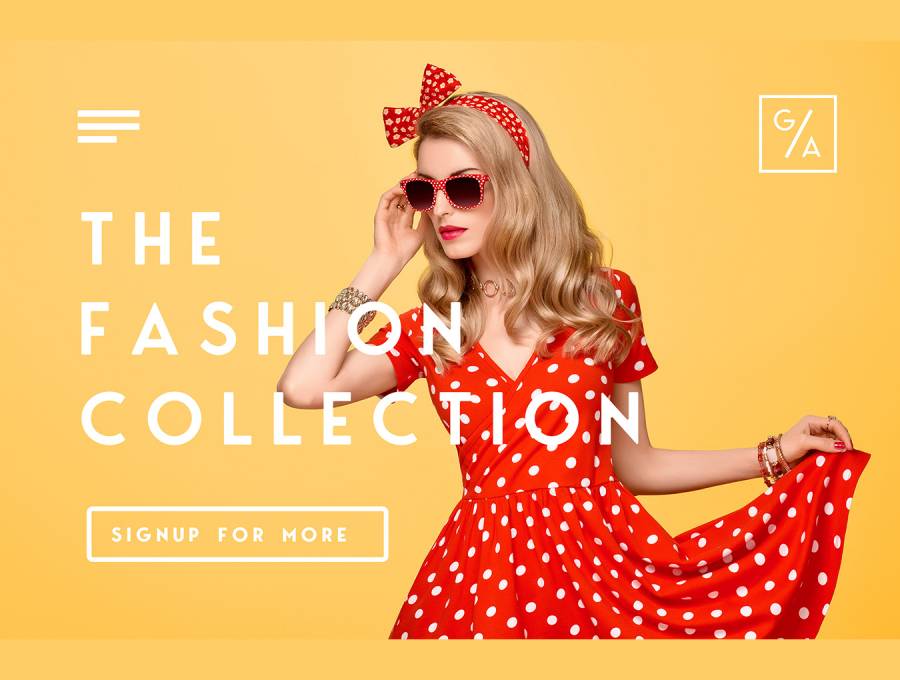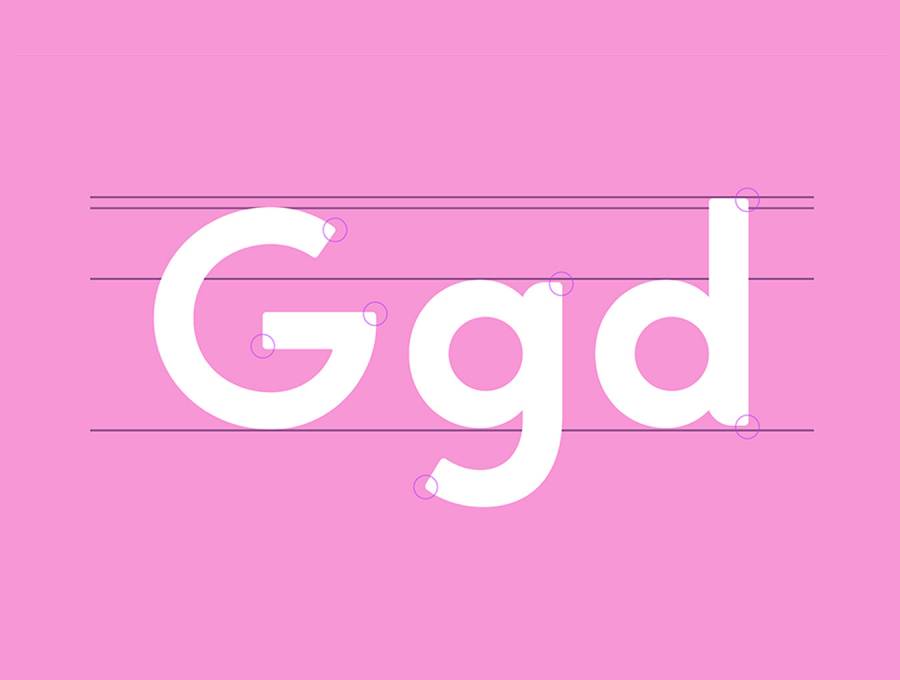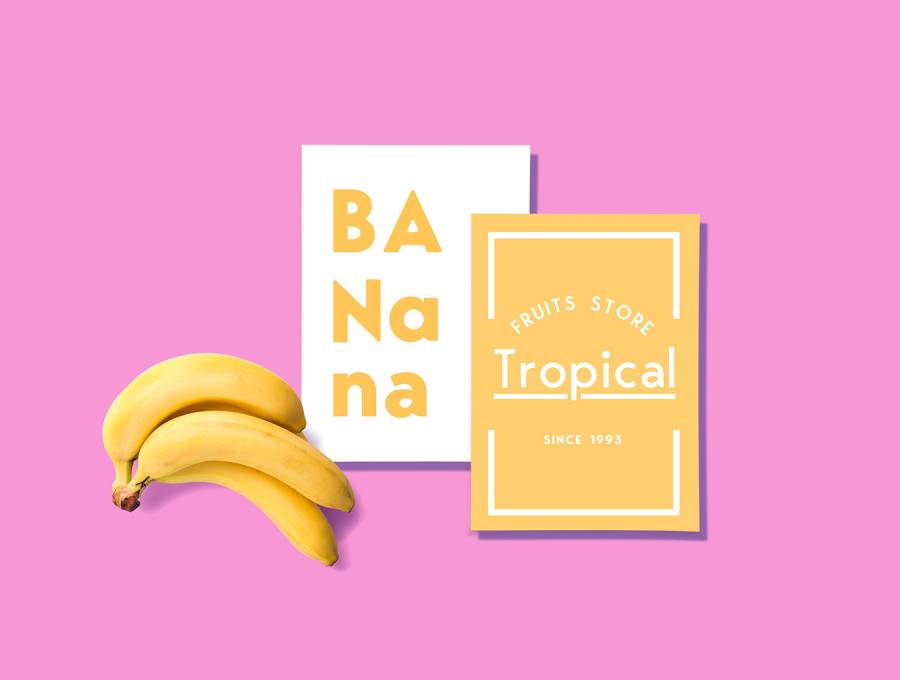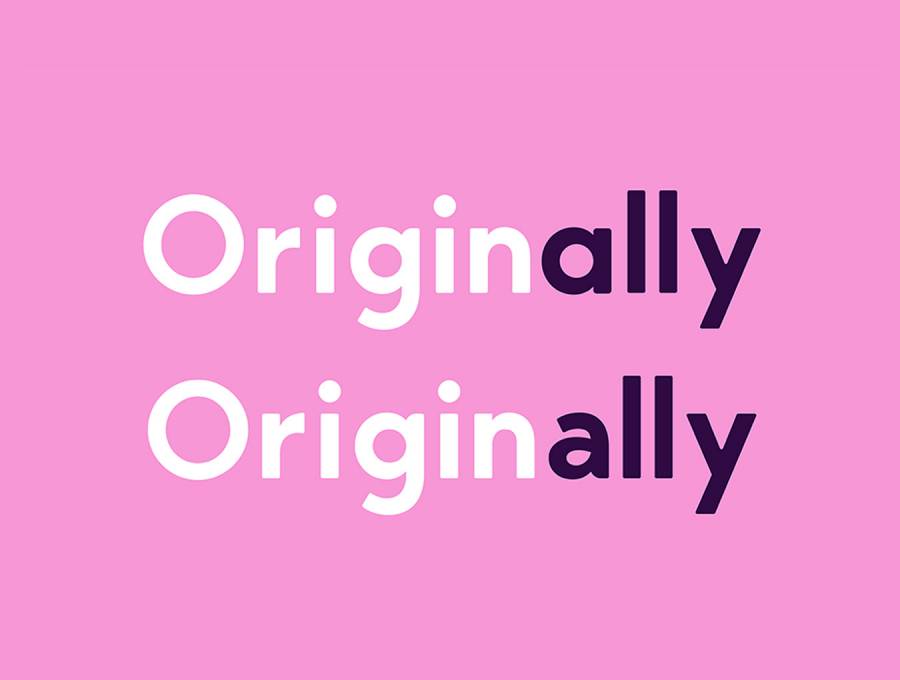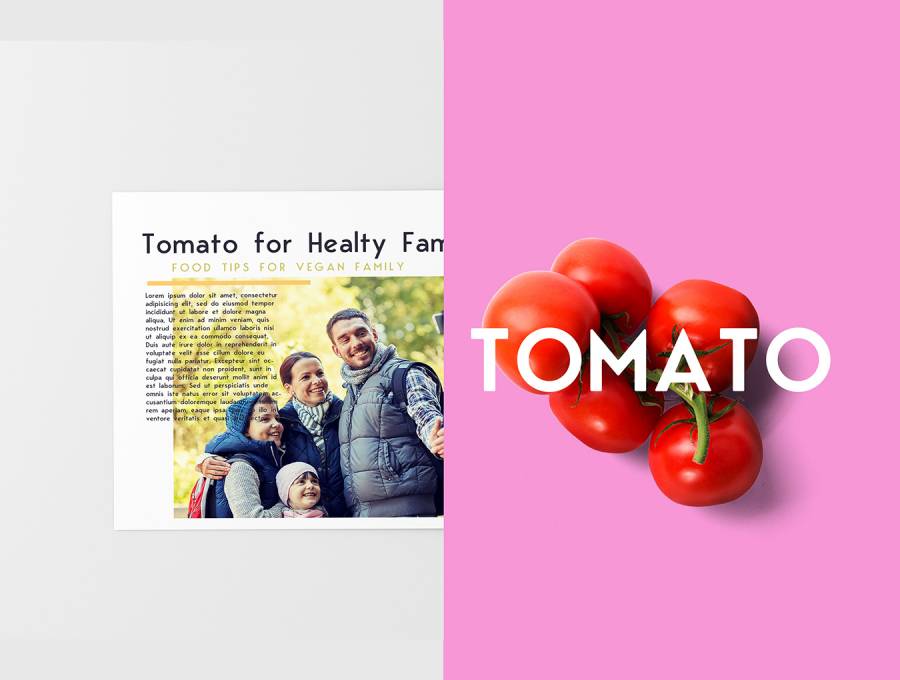
优雅的当代无衬线字体系列,带有柔软边缘的6种字体。,George Round Sans Serif字体
George Round v1.0是一款优雅的当代无衬线字体系列,由6种字体组成,带有柔软的边缘。采用干净,风格化的现代欧洲几何设计,文字和标题的和谐外观。 George Round是品牌推广,编辑和标牌的完美伴侣,也适用于更大的应用程序。 George Round还包括许多语言支持。